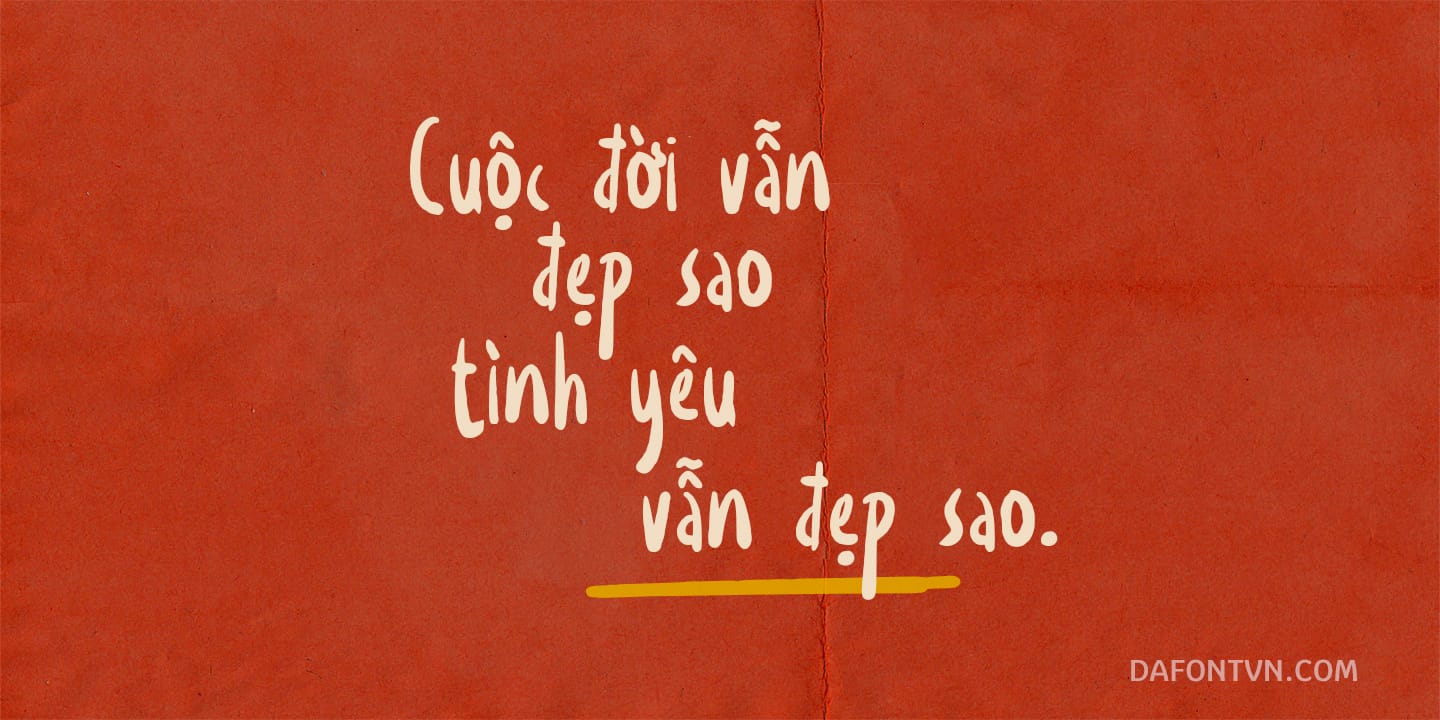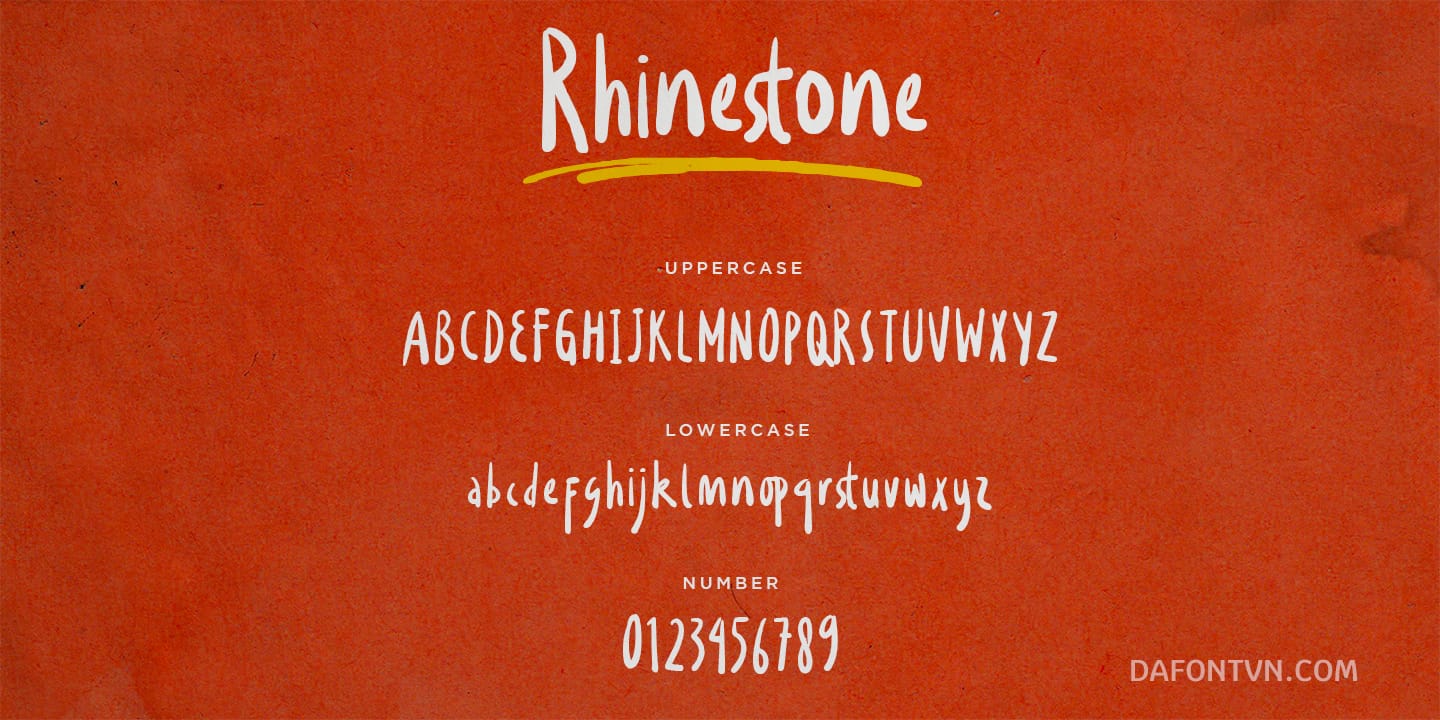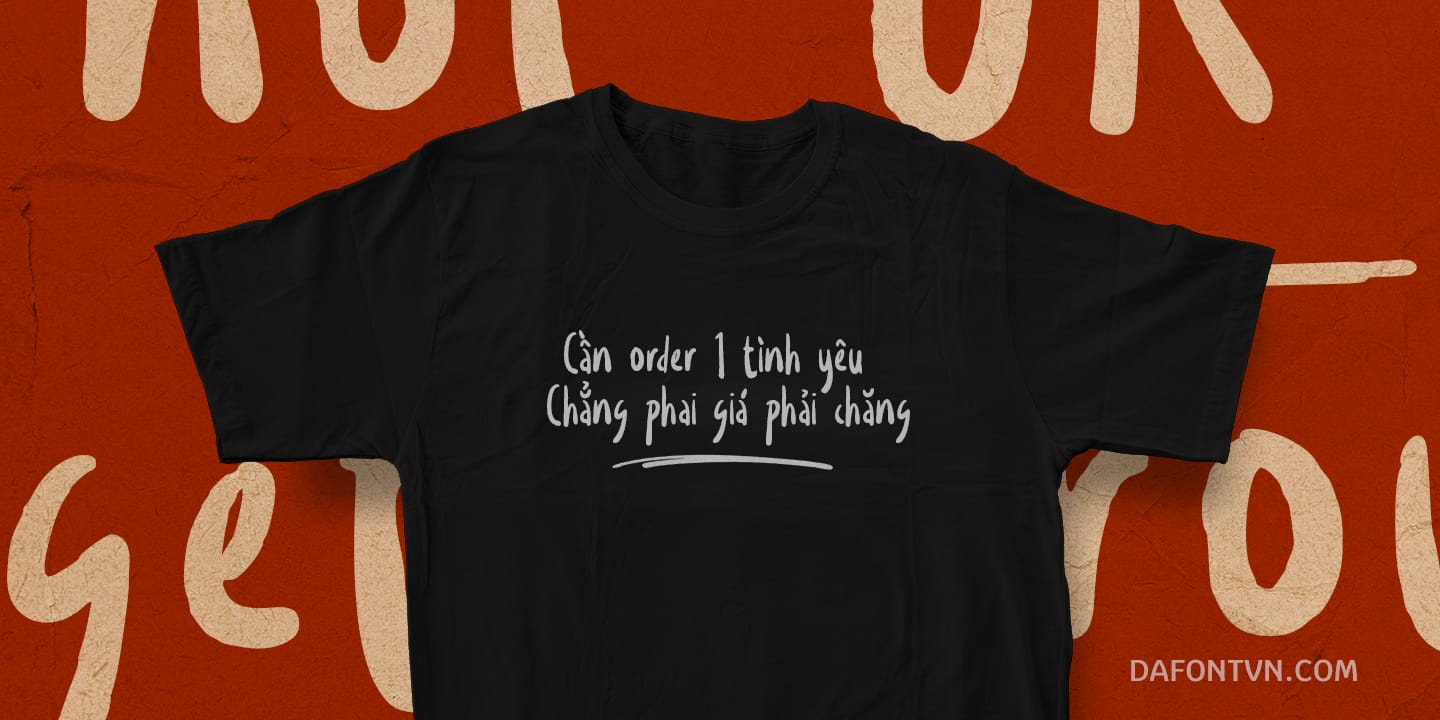
Font Rhinestone Việt Hóa – Font viết tay
Rhinestone là font chữ viết tay với các đường nét độc đáo.
Font chữ này được tạo ra với niềm vui, được thực hiện bằng cách sử dụng một brush tùy chỉnh để nó trông tự nhiên. Có chữ ghép và chữ thay thế để dễ dàng sử dụng. Font Rhinestone Việt Hóa chữ này có thể được sử dụng làm biểu trưng, sổ ghi chú hoặc thiết kế bao bì hoặc v.v.